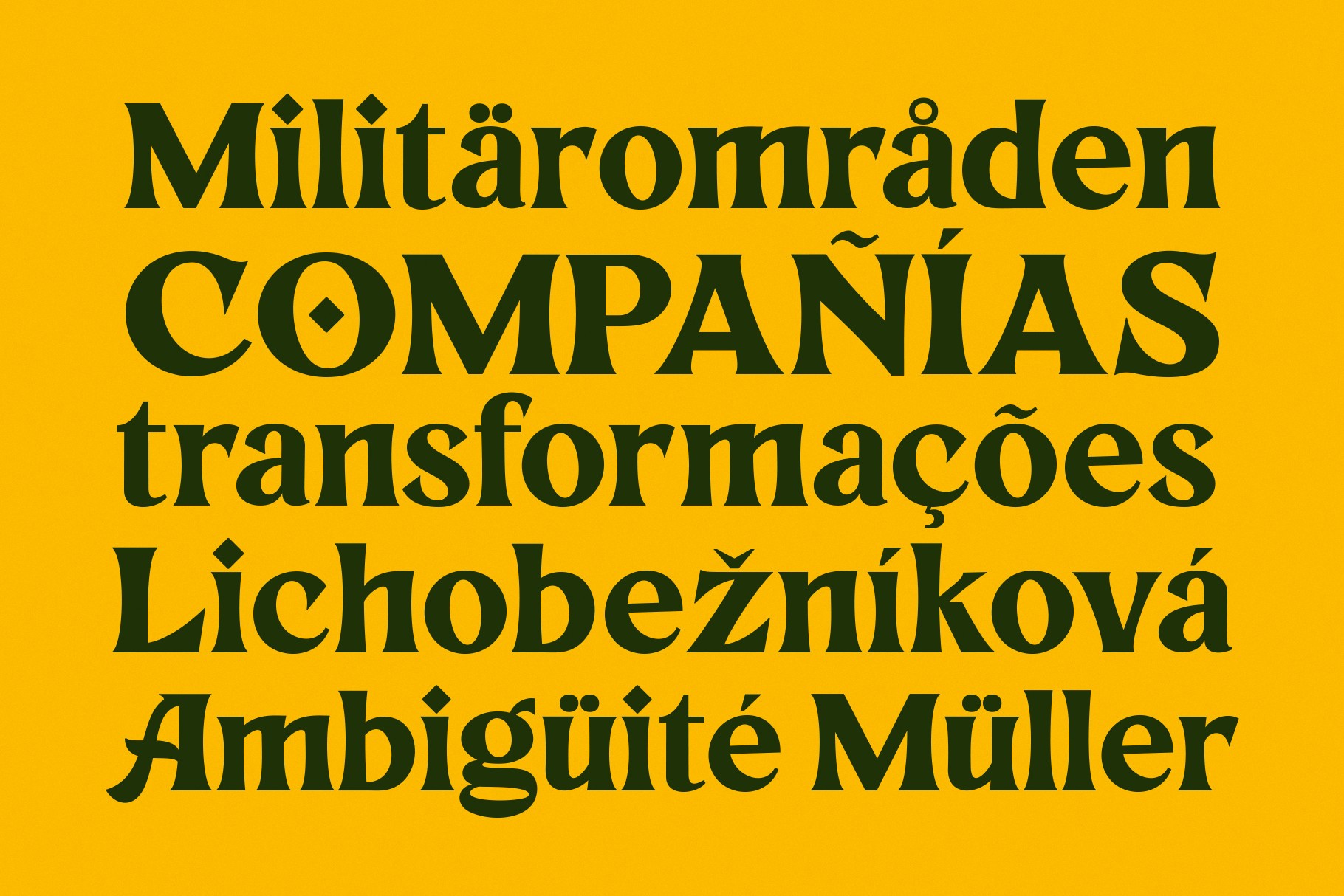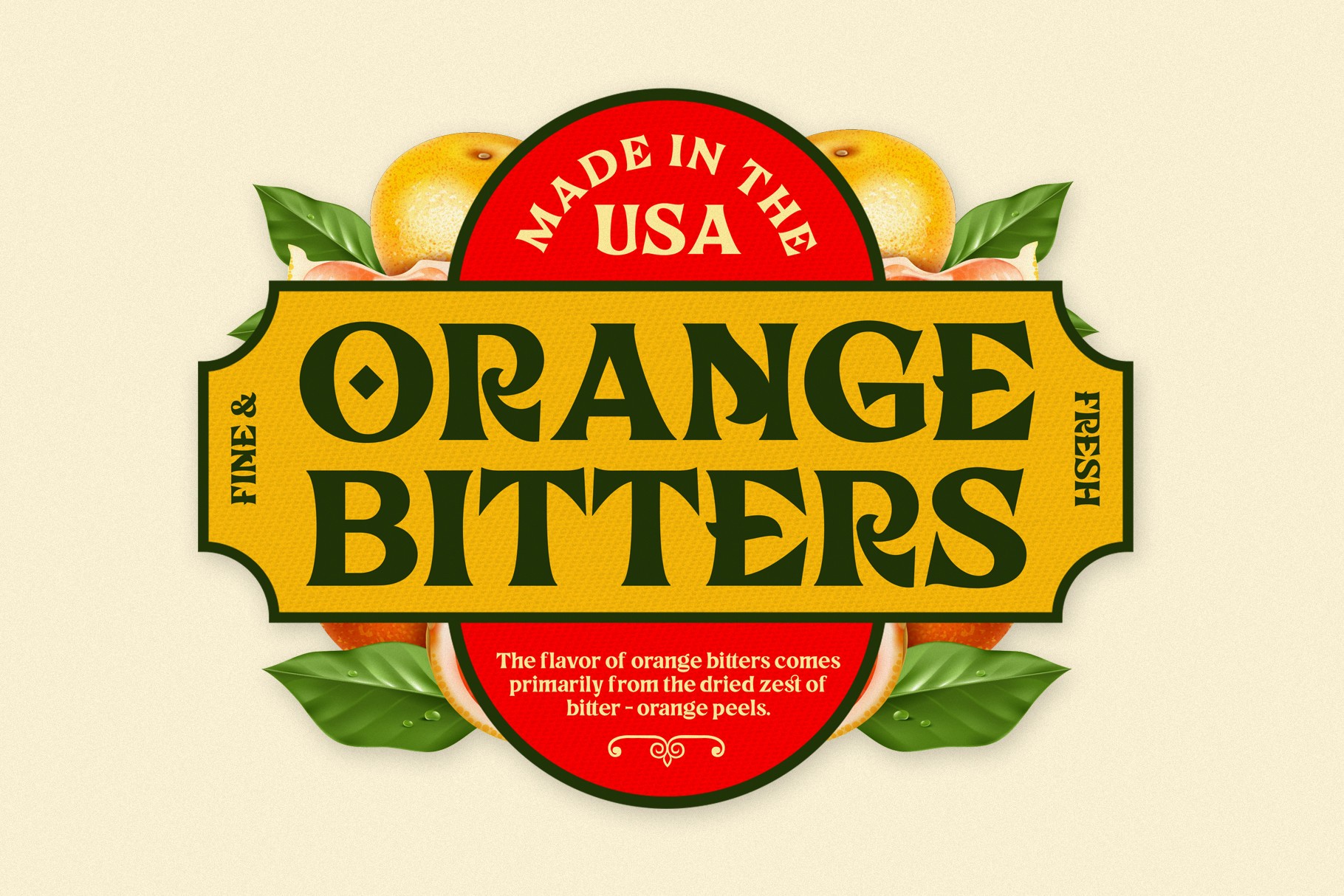
Rhinegold Font
Description de Rhinegold Font
Rhinegold est un présentoir de polices réalisé à la main, inspiré des affiches classiques. Rhinegold est livré avec des majuscules, des minuscules, des chiffres, des signes de ponctuation et de nombreuses variations sur chaque caractère, notamment des alternatives de type ouvert, des ligatures communes et également un swash supplémentaire pour vous permettre de personnaliser vos créations. Parfait à utiliser pour le logotype, le papier à en-tête, l’affiche, la conception de vêtements, l’étiquette, etc.